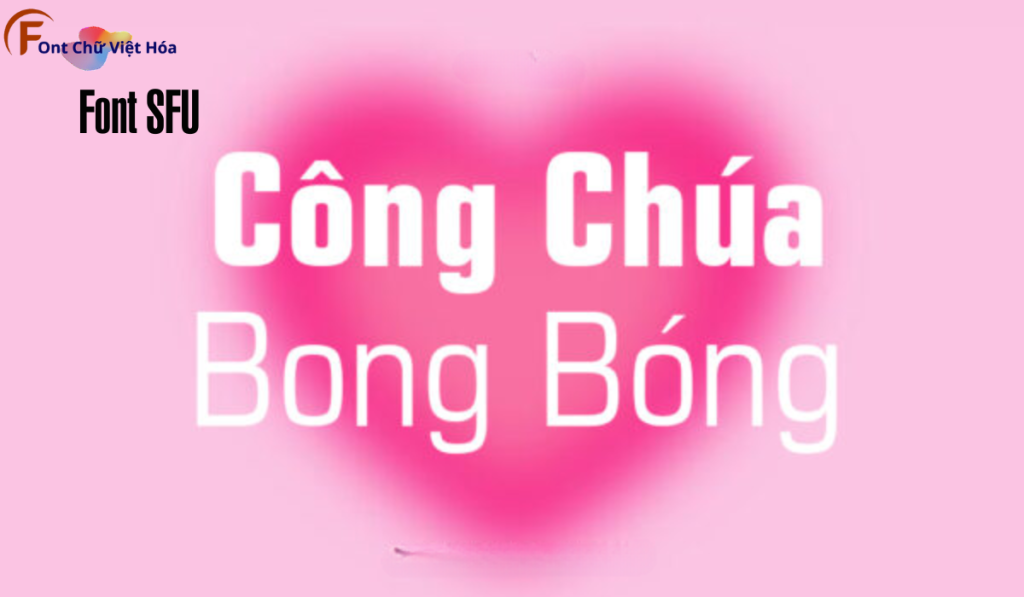
SFU Eurostile Font Việt Hóa
Tác giả: Urs Felber
Bộ Font: SFU
Độ dày: Thin, Light, Regular, Medium, Bold, Heavy
Font SFU Eurostile Việt Hóa là một font chữ độc đáo, mang phong cách sans-serif hiện đại với các đường nét mạnh mẽ và cá tính, thuộc bộ font SFU. Thiết kế của SFU Eurostile tập trung vào sự rõ ràng và dễ đọc, đặc biệt phù hợp cho các thiết kế đòi hỏi tính thẩm mỹ cao như poster, logo, và tiêu đề. Với tỷ lệ chữ cân đối và các đường nét đậm, font này tạo ra ấn tượng thị giác mạnh mẽ và giúp tối ưu hóa không gian trong thiết kế. Font này cũng đã được Việt hóa, mang đến sự linh hoạt và tiện dụng cho các dự án thiết kế bằng tiếng Việt.